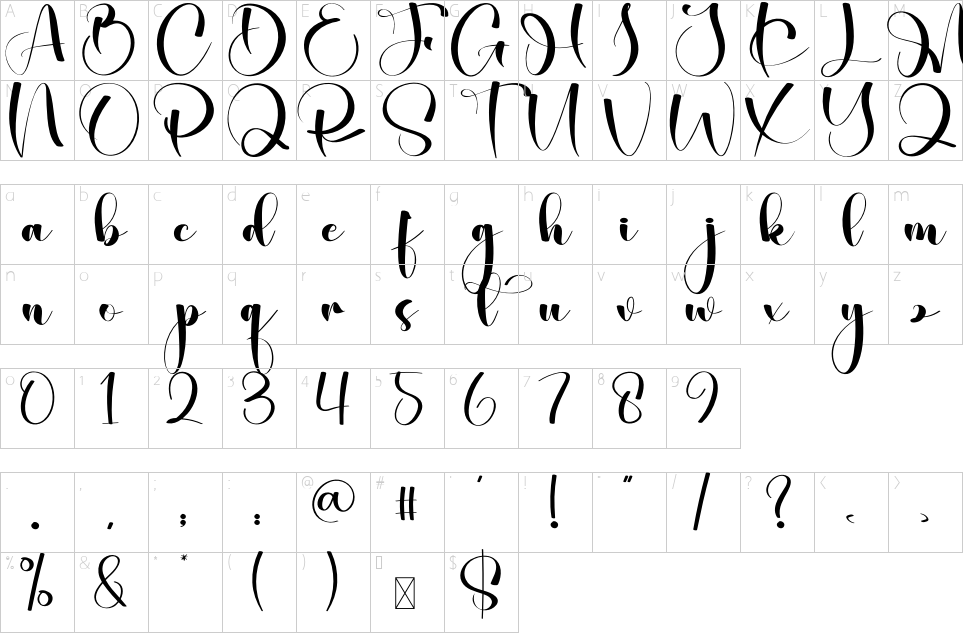
A Mongolia Font é uma fonte de graça que traz um toque de cultura árabe para seus projetos. Desenvolvida pelo designer não informado, a Mongolia Font é uma escolha ideal para quem procura um estilo único e intrigante para o seu design. Com uma arquitetura de letras que é tanto expressiva quanto sofisticada, esta fonte é perfeita para títulos e headlines em portfólio de design, aplicativos e identidades de marca. Não importa o tipo de projeto, a Mongolia Font está sempre pronta para dar uma nova dimensão ao seu trabalho, oferecendo uma variedade de opções para usar em diferentes formatos e tamanhos. Download a Mongolia Font hoje e dê um toque de modernidade e originalidade à sua próxima criação.